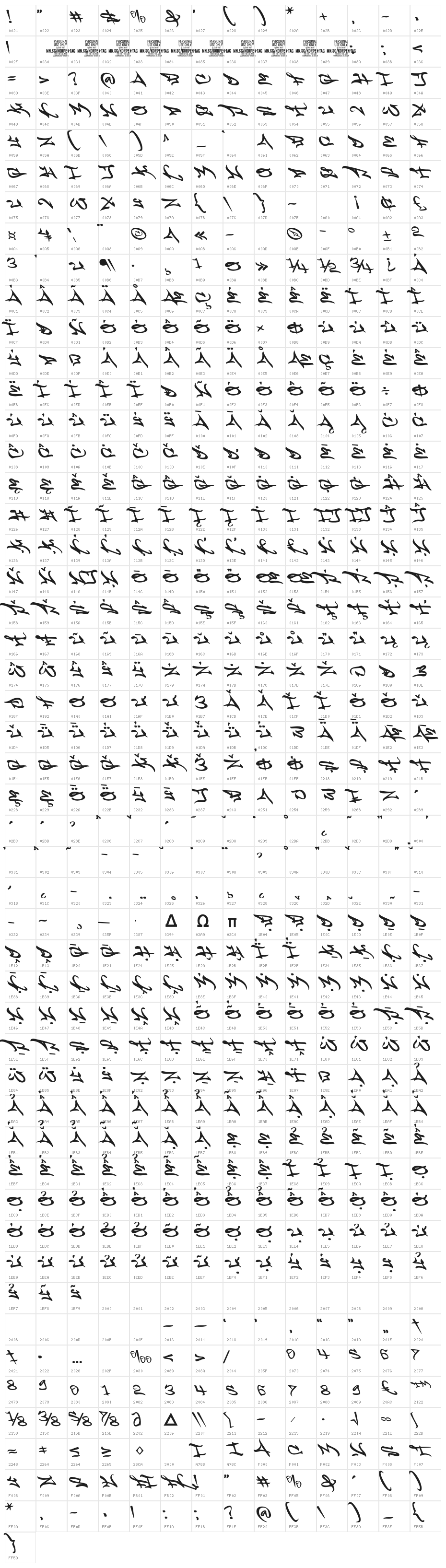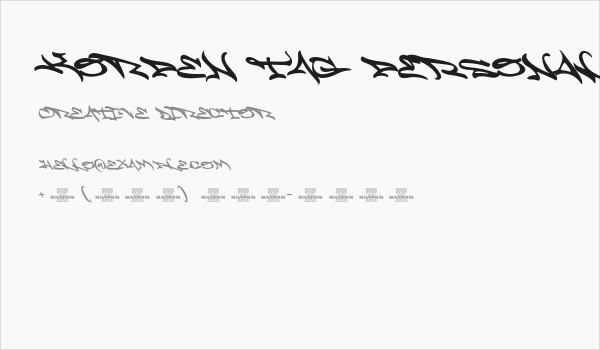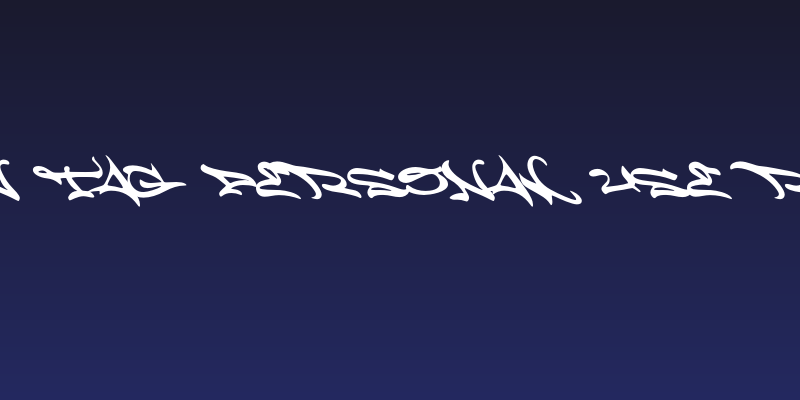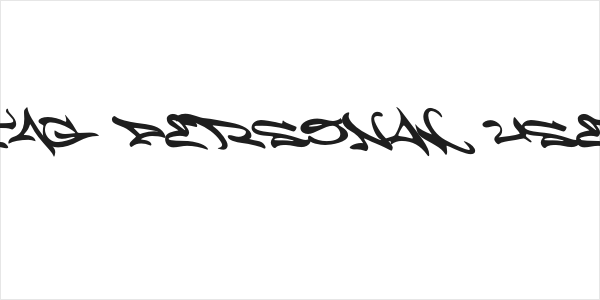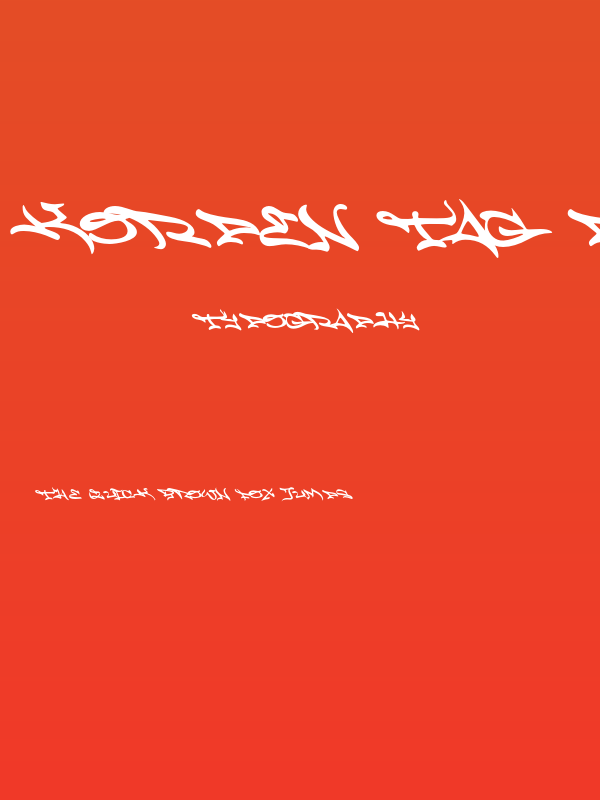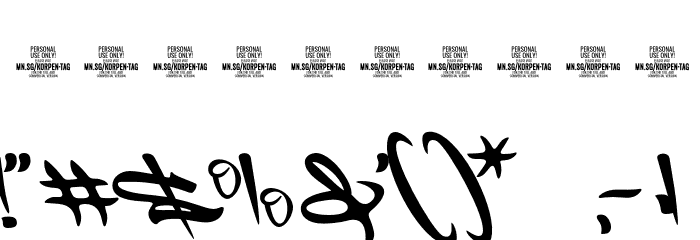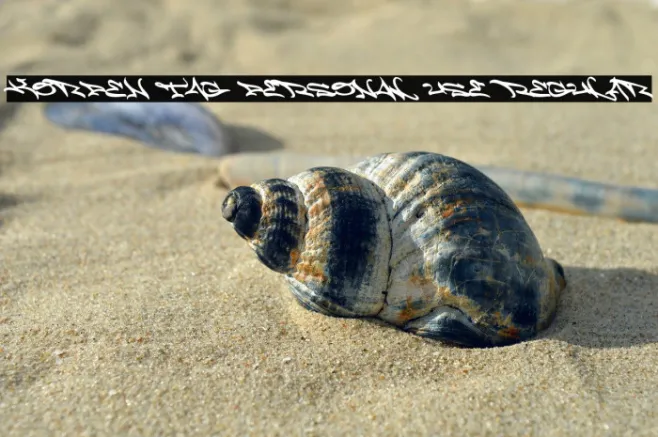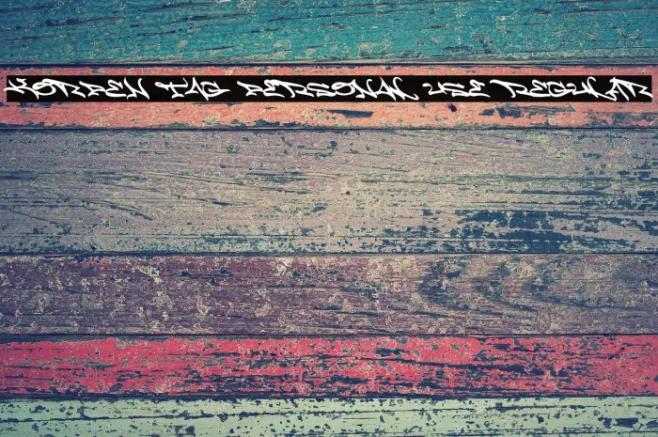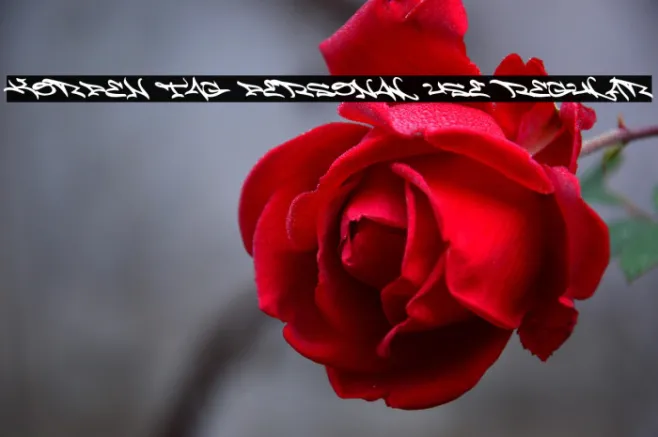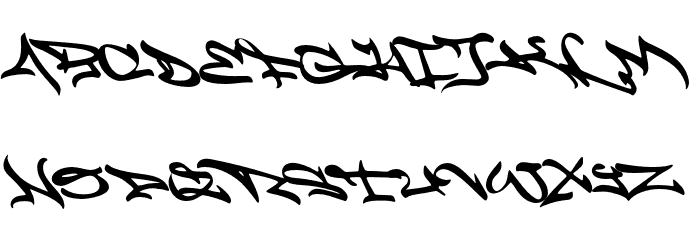
Korpen Tag PERSONAL USE Regular Font
✎ Graffiti
| Gesamtstil | Urban, Edgy, Graffiti |
| Anwendungsfall | Logos, Posters, Album Covers |
| Vorgeschlagene Projekte | Ideal for street art designs, urban-themed posters, music album covers, and edgy branding projects. |